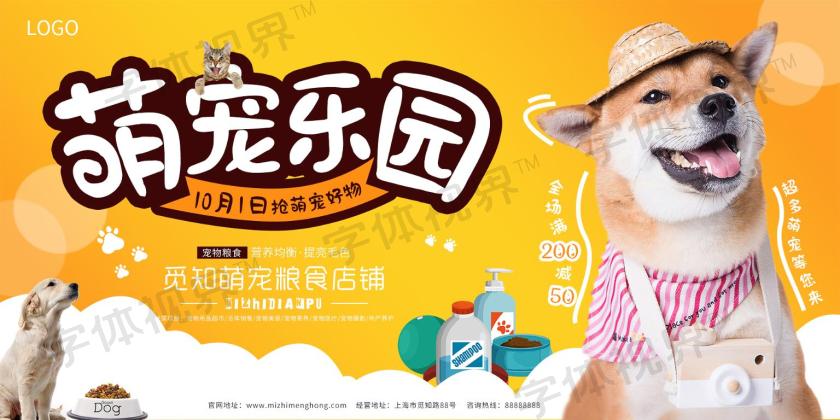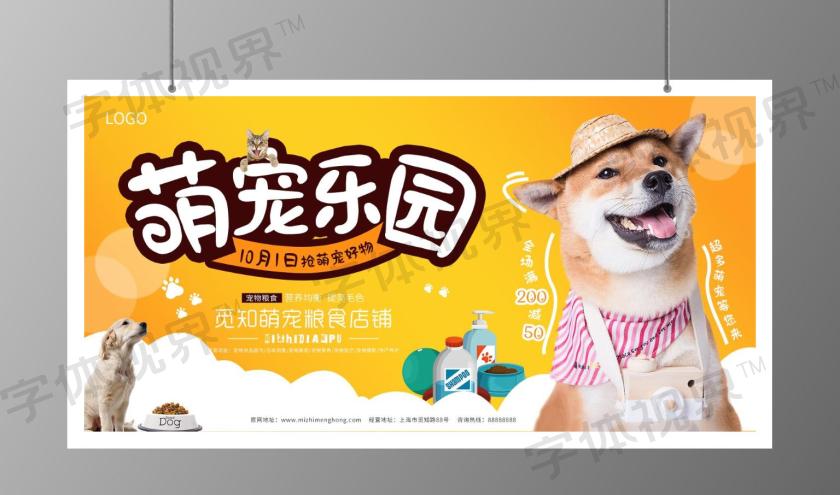
萌宠乐园活动宣传展板
这是一张关于宠物店活动宣传展板设计图片,可爱风格设计,以黄色为主色调,设计成宠物店活动宣传展板模板,主体文字图片皆可替换修改,也可用于宠物店活动宣传展板、活泼展板、萌宠展板、乐园展板、宠物店活动展板、宠物展板、店活动展板、宣传展板、活动展板、乐园宣传展板、宠物宣传展板、宠物店展板、宠物活动展板、宣传活动展板、店宣传展板、活动宣传展板模板素材,萌宠乐园活动宣传展板,格式为PSD,作品编号:511221,尺寸为2953*1476像素,欢迎会员免费下载。